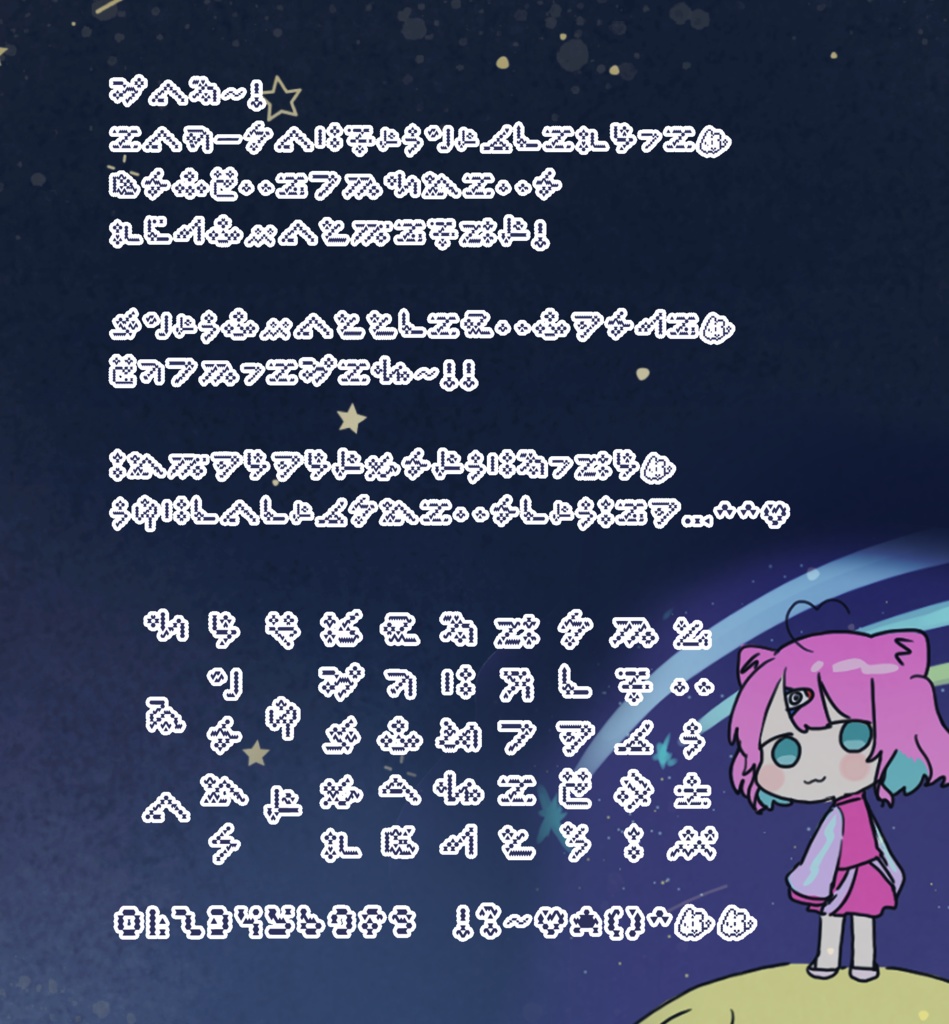
〖ぽるぷ文字〗UuU font
ぽるぷ星の言語フォント 【UuU_font】 を公開&配布します! 日本語のひらがなに似た独自の創作フォントです。 ぎりぎり読める…?くらいなので、他の文明の文字として、又は怪文書を作りたい方などのお役に立てるかと思います! .˚⊹⁺‧┈┈┈┈┈┈┈┈┈┈┈┈┈┈┈┈┈┈┈┈┈┈┈┈┈‧⁺ ⊹˚. 収録文字⤵︎⤵︎ ・ひらがな┊︎50音+濁点、半濁点、半音 ・数字┊︎0〜9 ・記号┊︎ 、。…ー〜!?()^♡☆ .˚⊹⁺‧┈┈┈┈┈┈┈┈┈┈┈┈┈┈┈┈┈┈┈┈┈┈┈┈┈‧⁺ ⊹˚. 【OK】 ・商用、非商用を問わず利用可能 ・同人活動での利用 ・加工しての利用 【NG】 ・公序良俗に反すること、政治的、宗教的な目的での使用 ・他者、特定団体への攻撃や誹謗中傷を目的とした利用 ・当フォントのデータをそのまま、又は改変したものをインターネットで公開する/第三者に配布する行為 また、フォントの素材データの著作権は作者である『侑夢うゆ』『動く点P(ゼラ)』が有しています。 ▪製品を使用して発生したいかなる障害および事故等について作者は一切の責任を負いません。